InDesign/Illustratorには[文字ツメ]という機能があります。前回触れたトラッキングが一律詰めであるのに対して、[文字ツメ]では文字ごとに詰め量が変わります。
[文字ツメ]はパーセンテージで指定しますが、これは「サイドベアリングを何パーセント削るか」を意味しています。たとえば[文字ツメ]100%では、サイドベアリングを完全に削ります。これは前後の文字とバウンディングボックスがぴったり接する状態です。
名前が[文字ツメ]なので、わたしがInDesignを使いはじめたばかりのころには、いわゆる詰め組みを実現するための手段として試してみたりしましたが、あまりうまくいきませんでした。もともとプロポーショナルで設計されている欧文のサイドベアリングも削ってしまうので、仮名に合わせて詰め加減を設定すると、欧文は詰めすぎになります。
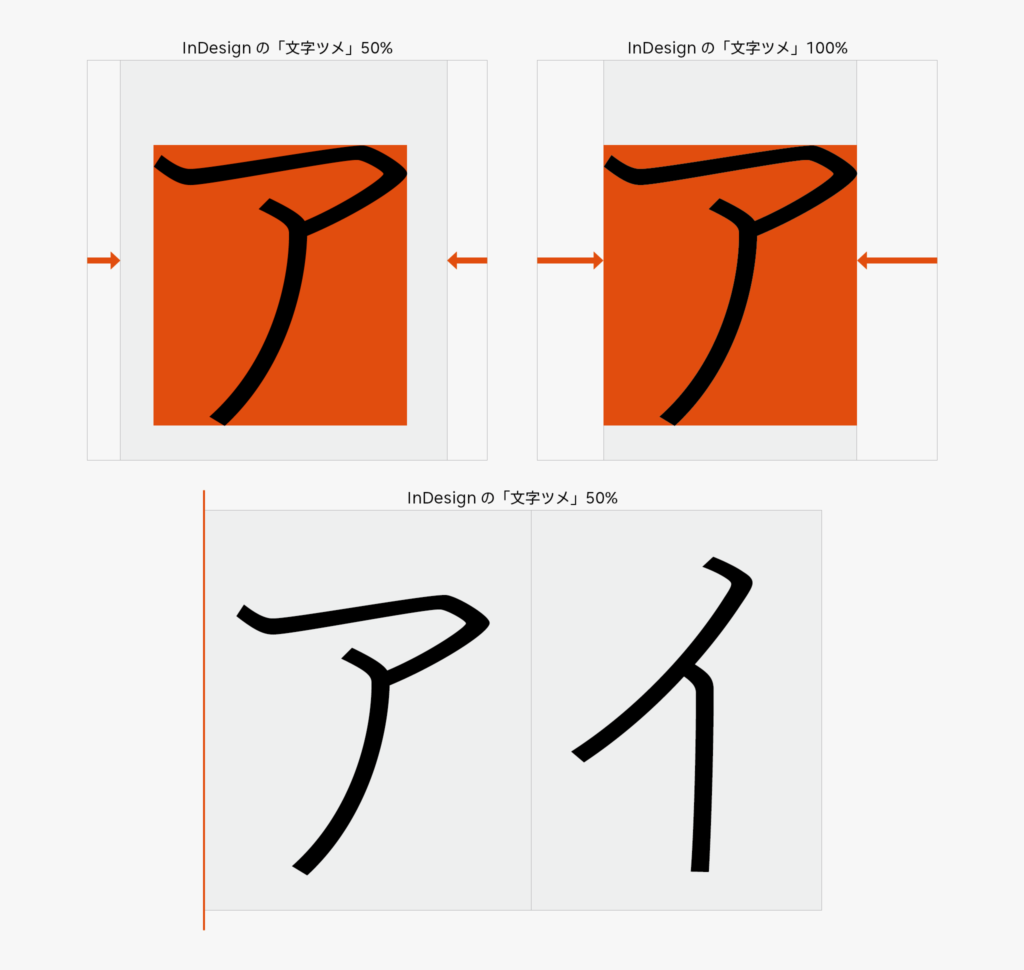
では、詰め組みのためには何を使えばよいのかというと、おすすめは[プロポーショナルメトリクス]プラス[カーニング(メトリクス)]です。詳しくは、このシリーズの続きでお話しします。